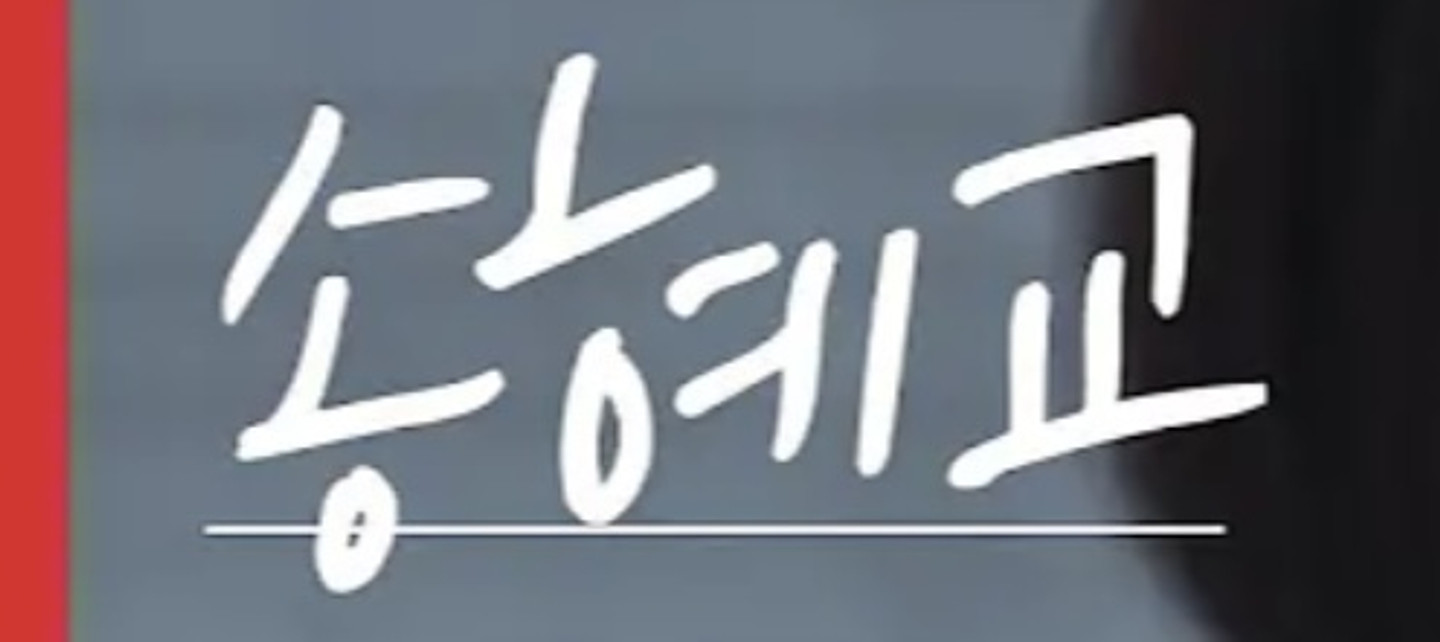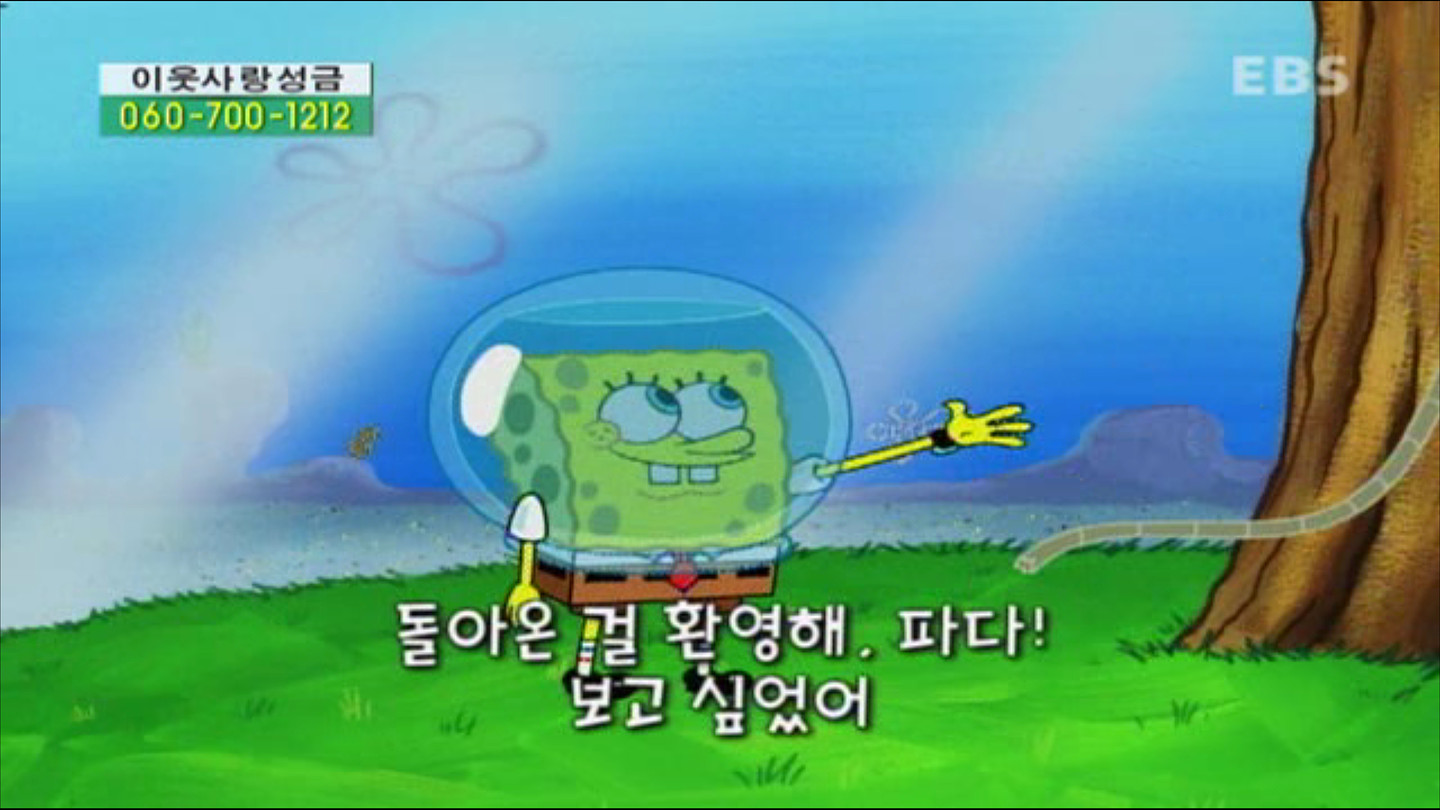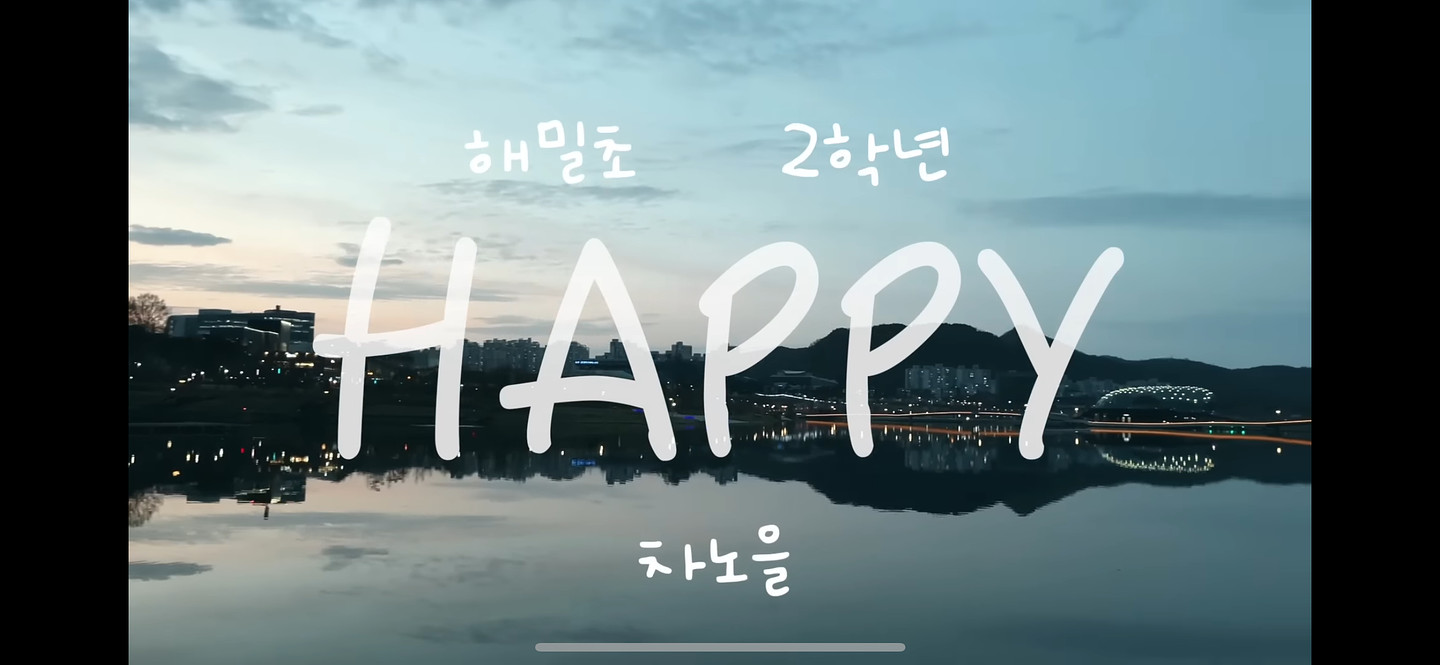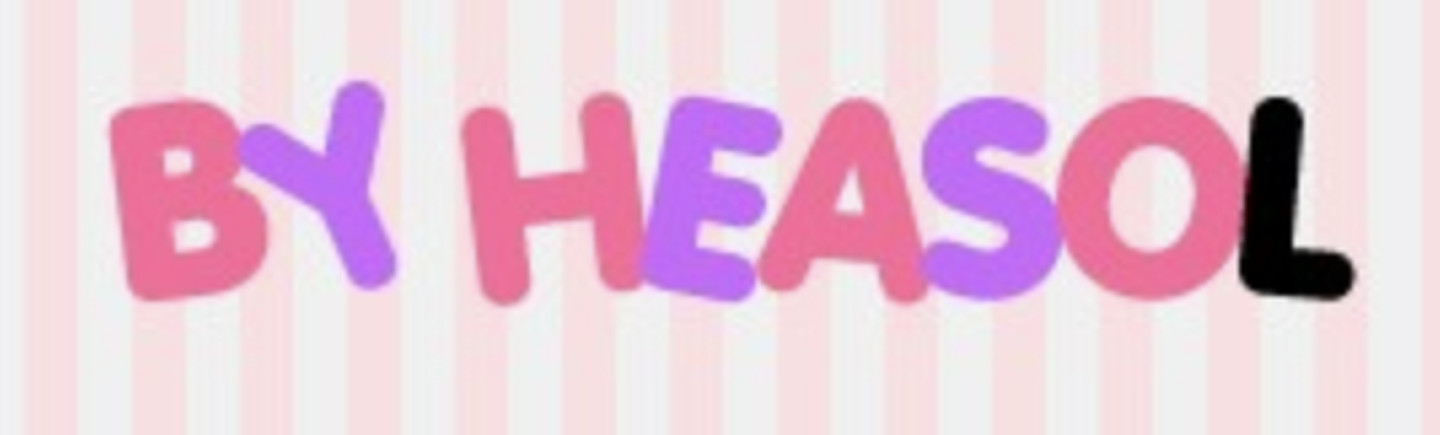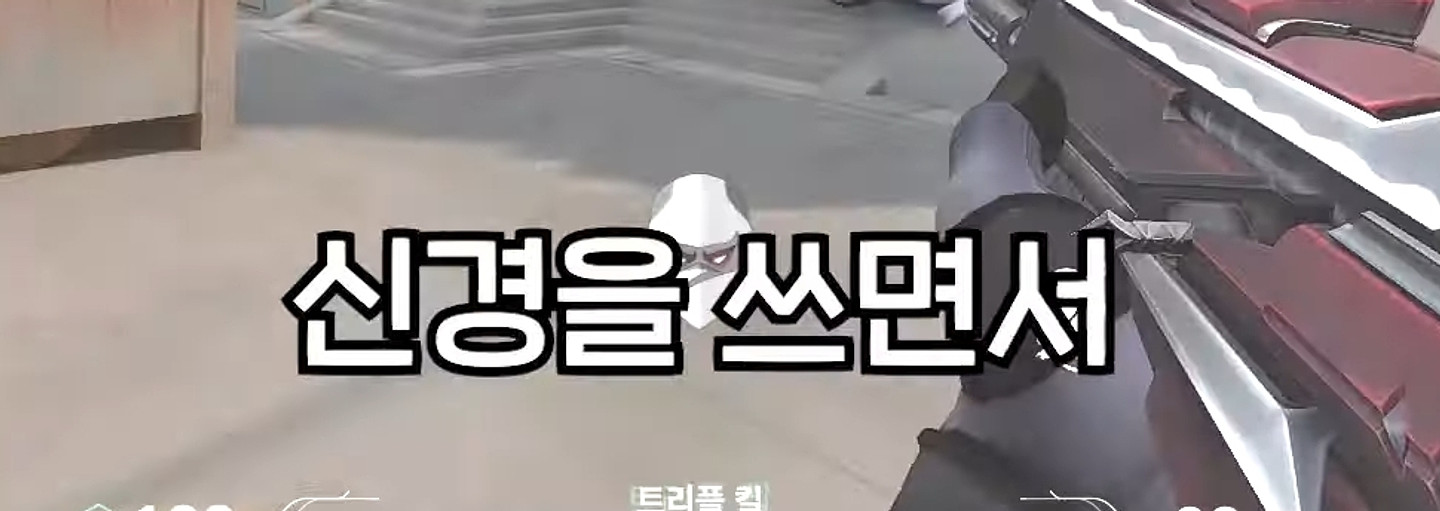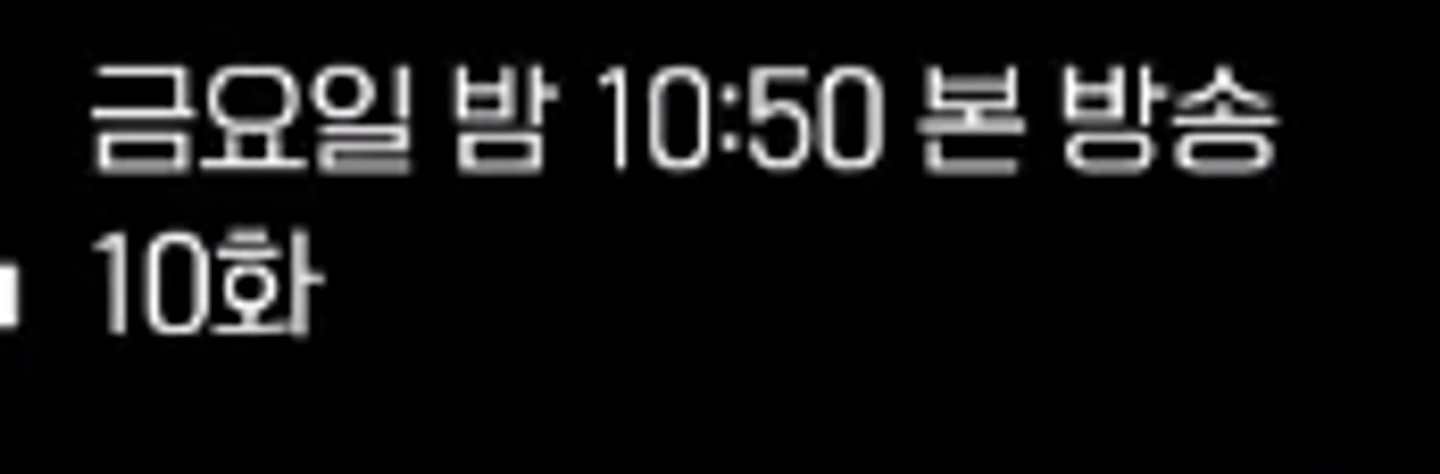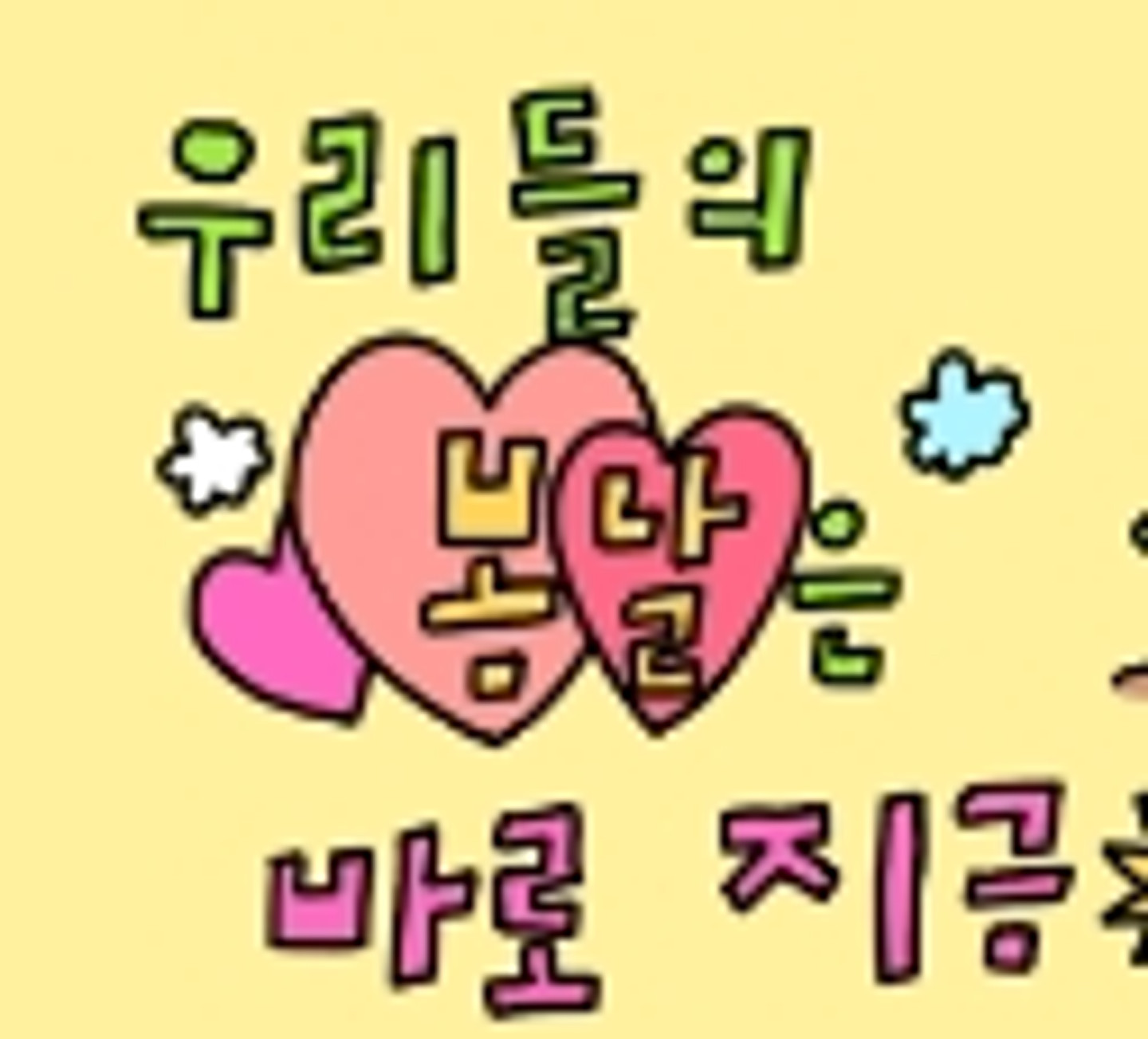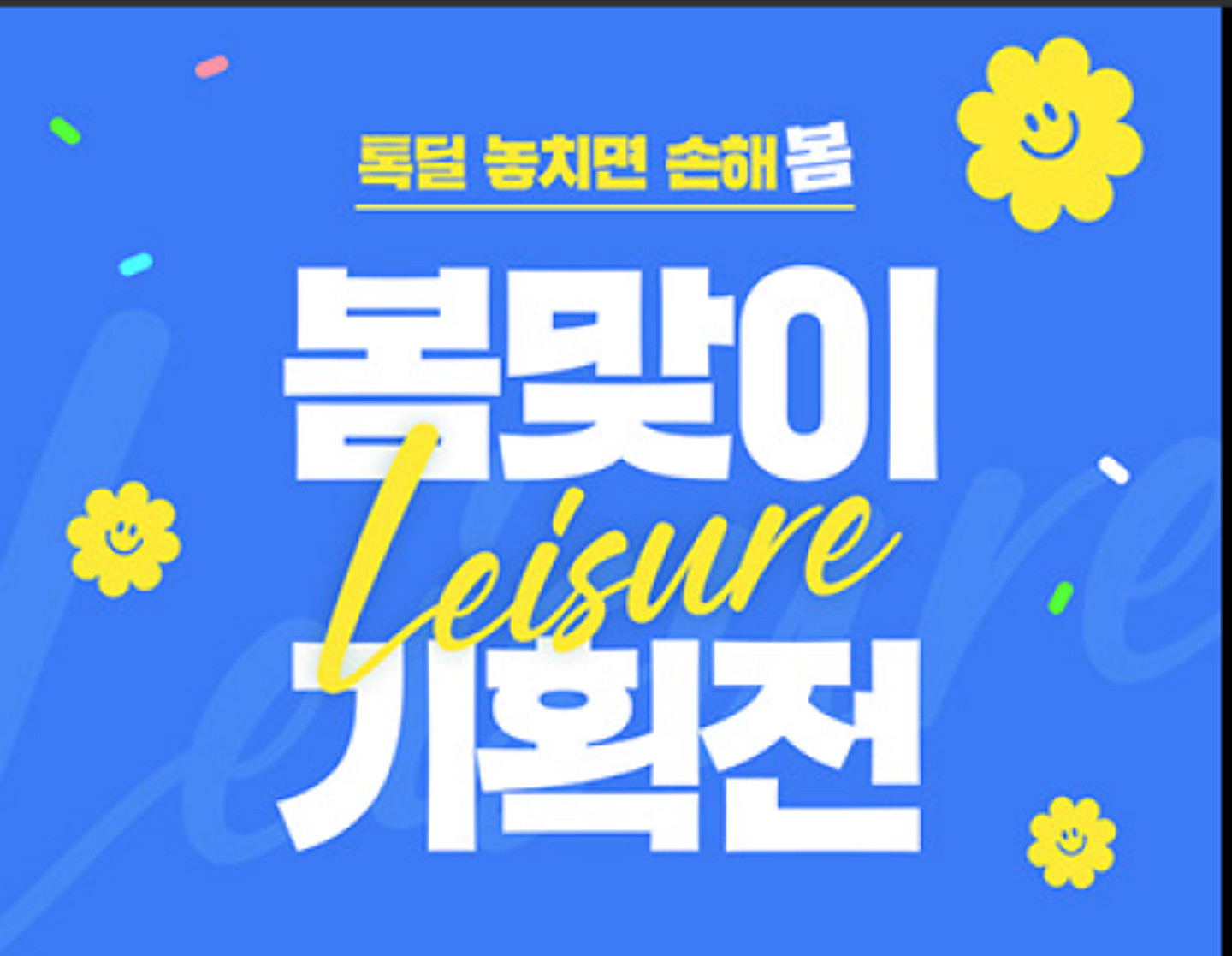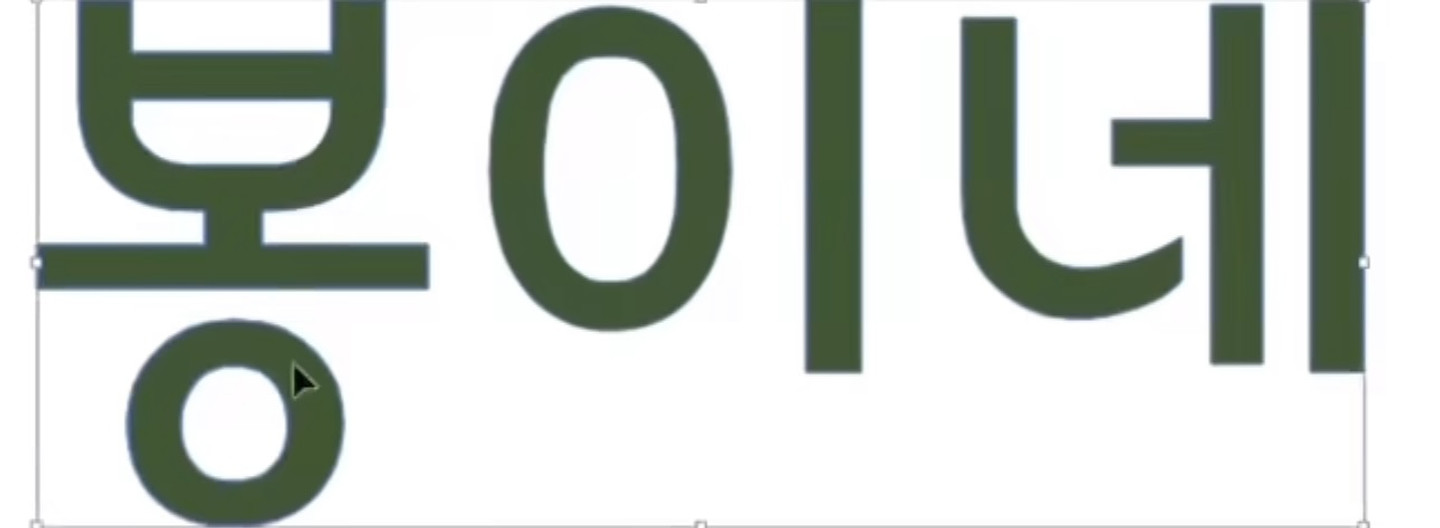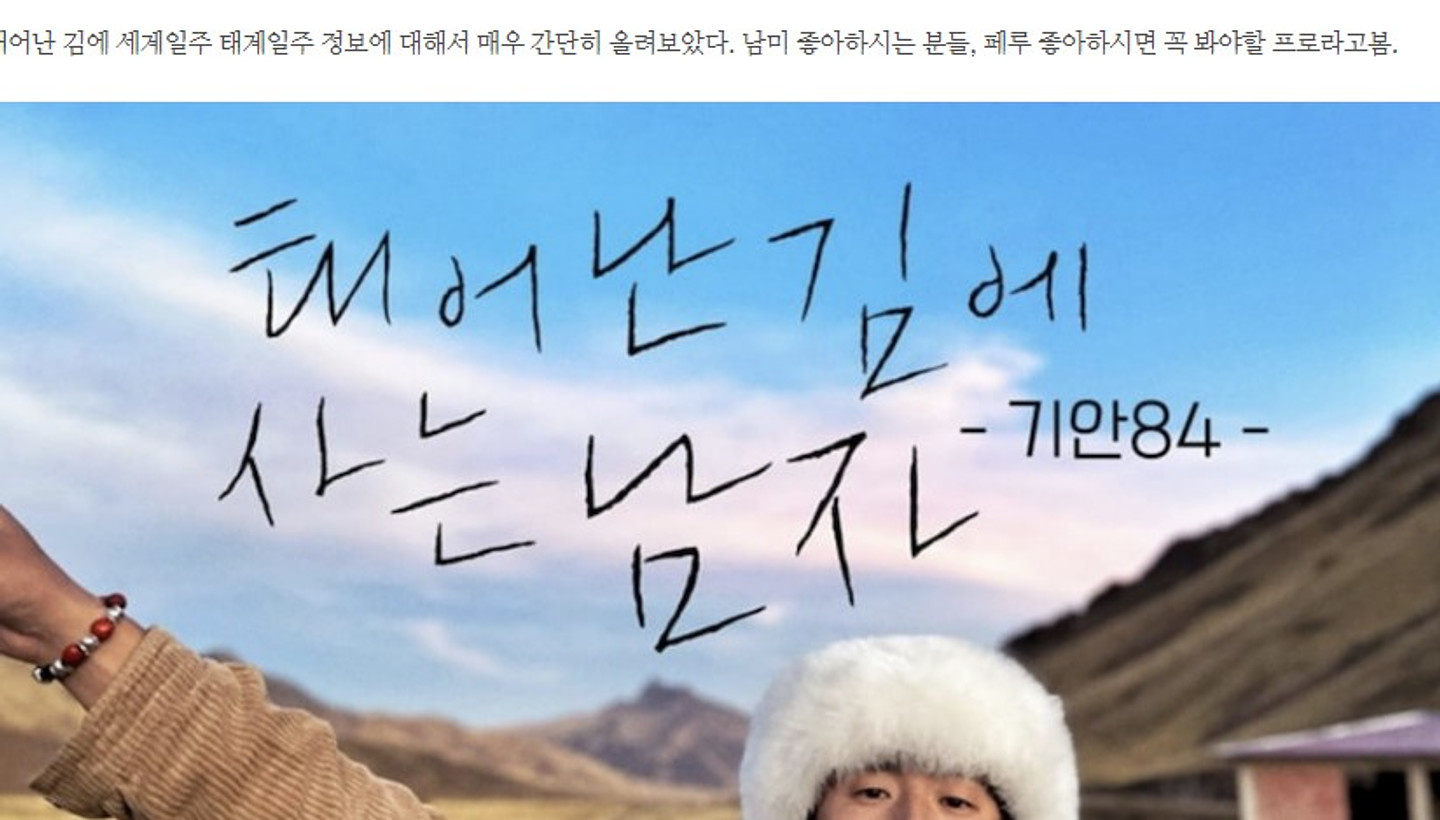
이 폰트 뭔가요??ㅜㅜ
이 폰트 이름 제발 알려주세요 ㅠㅠ
이 폰트 뭐에요?
폰트이름 궁금해요
이거 무슨 폰트인지 알 수 있을까요?
무슨 폰트일까요???
이거 뭔지 아시는 분?
이미지 내에 있는 영문 폰트가 궁금합니다. 해당 폰트와 유사한 느낌의 폰트가 있다면 추천해 주시면 감사드리겠습니다 :-)
뜬뜬에 나오는 폰트 같은데 무슨 폰트일까요..? 이미지로 검색해봐도 '약간'이라는 폰트에 ㅑ 와 ㄱ이 저런식으로 붙어 있는 폰트가 잘 안보이네요ㅜㅜ
이거는 좀더 부드러운 느낌인거 같은데 무슨 폰트 일까요?
약간 거친느낌? 글자에 거뭇거뭇 한것들이 있는 느낌이 좋네요 무슨 폰트인가요?
요고 폰트 먼가용유ㅠ '??
이건 무슨 폰트 일까요?
무슨 폰트일까요+.+?
이거 폰트가 뭘까요ㅠㅠ?
요거 무슨체인가요?
무슨 폰트인지 아시는 분 있나요?
무슨 폰트인지 알려주세요ㅠㅠ
어떤 폰트인가요? 손글씨일까요?
노란색 폰트 아시는 분 있으실까요?
이 폰트, 아시는분 계실까요?
무신사 폰트 알려주세요
ㅗ자가 저렇게 둥글게 되는거 폰트 이름이 뭔가요 ??
어떤 서체인지 궁금합니다~ 부탁드립니다^-^
여기 스타벅스 폰트 뭔지 알수있을까여??
무슨 폰트일까요ㅠㅠ
위아래 글씨체 같은 서체인가요??? 무슨글씨첸지 알려주세요ㅠㅠ 전라북도체???? 인가요
고수님들 이거 글씨체 알수 있을까요.?.!
무슨 글씨체 일까요..?!? 두꺼운 고딕인데 저 찌부된 느낌이 좋아서 비슷한거라도...
무슨 폰트인가요..?
기본폰트인거같은데...알려주세용..
이 폰트 이름 뭔가요?
강태풍 잡기술 2탄애 나오는 폰트 아시는 분은 답글 남겨주세용 ^_^
무슨폰트일까요..
엔시티 위시 송버드 앨범에 사용된 별패턴 폰트 이름이 뭔가요?
'설' 에 사용 된 폰트가 뭔가요?
명조체 같은 느낌의 폰트
도당체 무슨폰트일까요 ㅠ 인스타 '푸드의 먹스타그램' 에서 사용하는 서체인데 너무 알고 싶어요! https://www.instagram.com/food._.slimee/
네이버 웹툰 격기 3반에 등장한 올드한 느낌의 한국 폰트입니다. 어떤 폰트인지 알 수 있을까요? 감사합니다.
포스터에서 birdcage 부분 폰트가 궁금합니다. futura, avant garde, avenir는 아니었습니다.
이거 글씨체 뭔가요 ㅠㅜㅠㅜㅠㅜ 테두리 없는 버전도 있나요? 있다면 그걸로 알려주세요 ......
안녕하세요! 이건 어떤 폰트인지 아시는 분 계실까요? ㅠ_ㅠ
이 서체가 무엇일까요? 고수님들 부탁드려요 감사합니다^^
ㅈ 이 가운데서 시작하는 요 글꼴 알려주실 수 있나용
폰트 궁금합니다 능력자분 알려주세요ㅠㅠ
안녕하세요 :) 해당 폰트 알고 계시는 분 있으면 정보 공유 부탁드립니다. 연말 잘 보내세요!
아시는 분 계시나요
스타벅스 폰트 뭔지 알려주세요ㅜ
폰트 이름이 궁금합니다 전문가분들 도와주세요!!
영문폰트 무엇이죠?
우튭 소올님 카톡 폰트 궁금합니다.!! 이폰트 뭔가여 ㅠㅠ
이런 영어 폰트 아시면 알려주세요 ㅠㅠ 부탁드립니당
숫자폰트인데 무슨 폰트인지 알 수 있을까요??ㅠㅠ